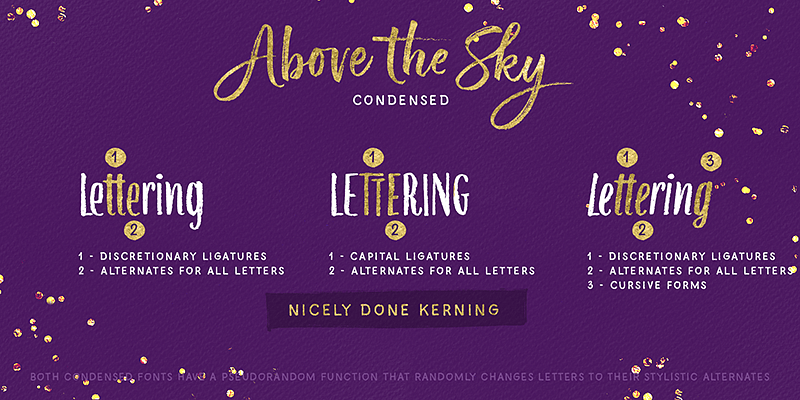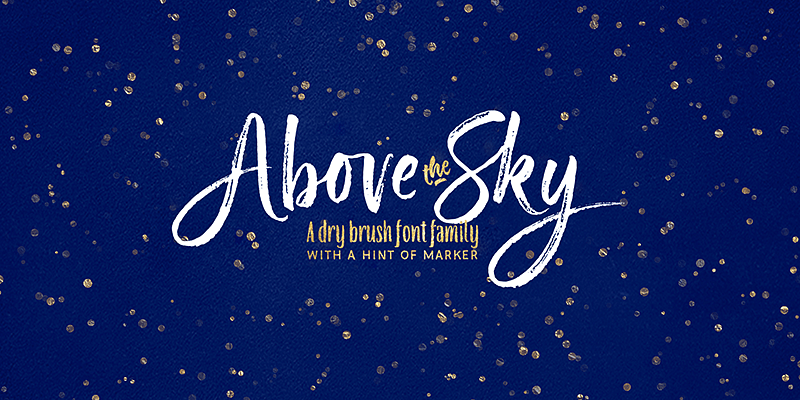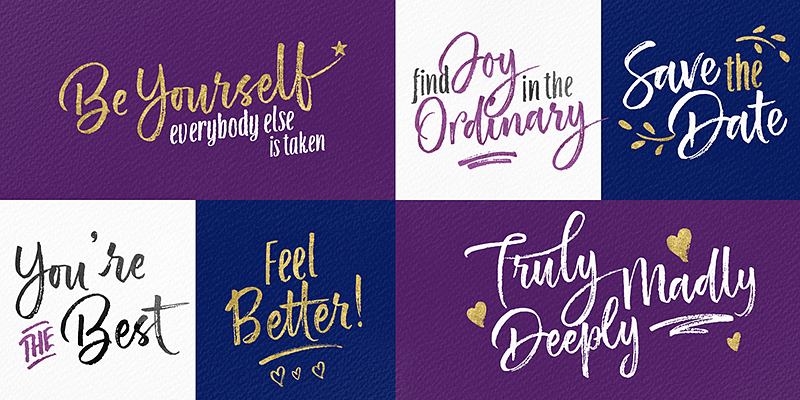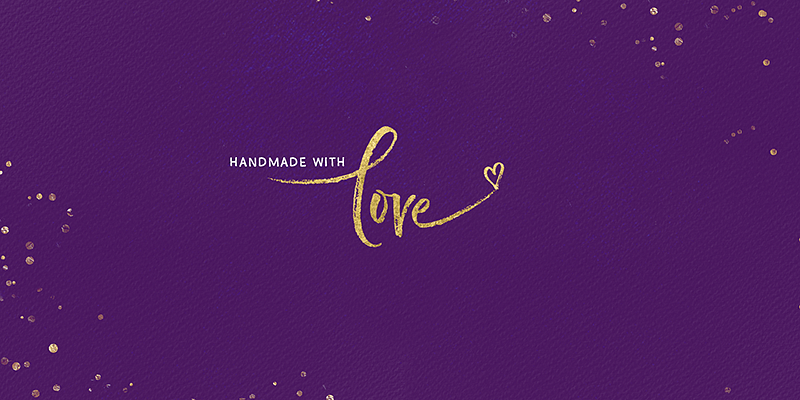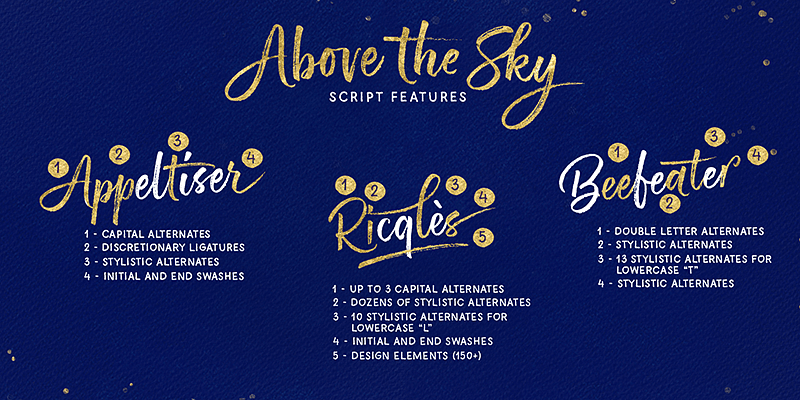
Dites bonjour à notre petite nouvelle, une famille de polices imitant la calligraphie au pinceau baptisée Above the Sky. Elle inclut enfin la version feutre toute en capitales que vous attendiez depuis si longtemps et que vous pouvez maintenant utiliser dans le texte « secondaire » de vos designs. Toutes les polices peuvent faire d’excellentes alliées pour les créations avec texte, la mise en forme de citations, le branding, le merchandising, les emballages, les invitations, les cartes de vœux, etc. Quand vous allez découvrir toutes les possibilités offertes par Above the Sky, vous allez être aux anges ! La version pinceau vous propose toute une myriade de caractères alternatifs, de ligatures et d’ornements, avec plus de 1 200 glyphes à votre disposition. N’hésitez pas à les combiner avec la version condensée et la version feutre pour un résultat du plus bel effet !